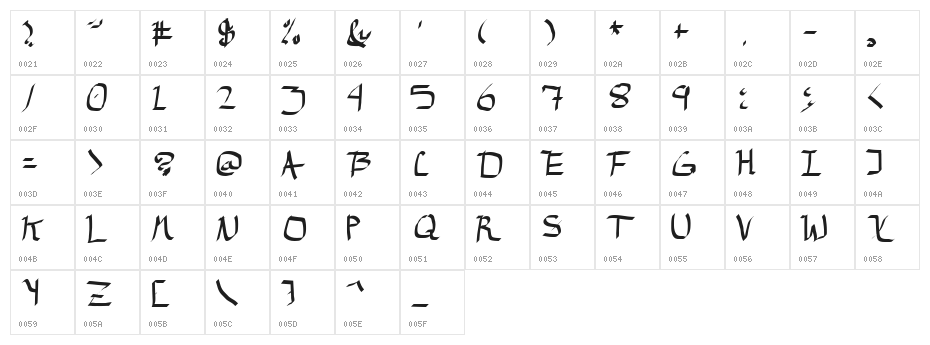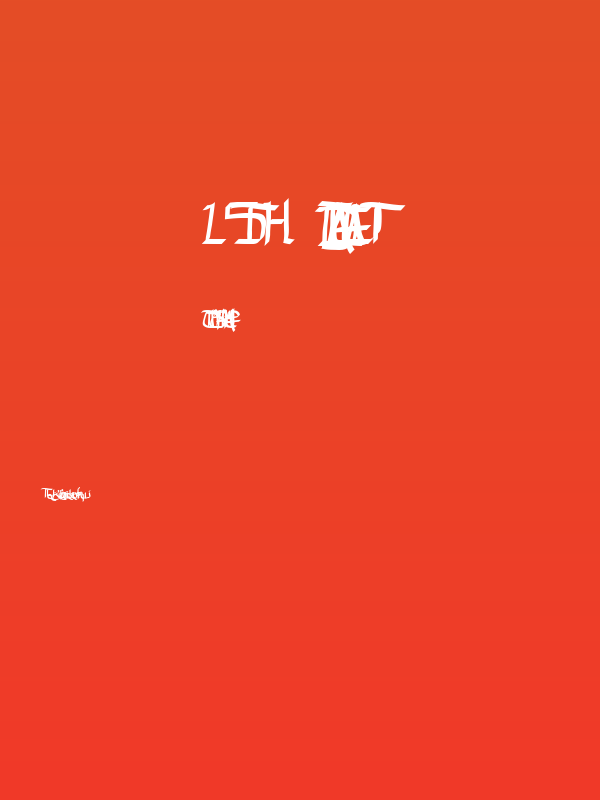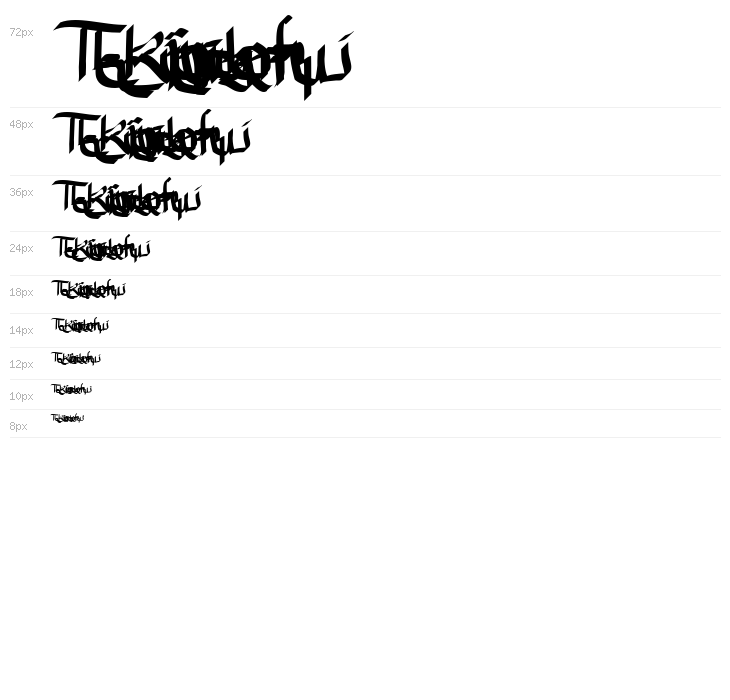
15th Accident Font
| Anwendungsfall | Logos, Headlines, Artistic projects |
| Vorgeschlagene Projekte | Ideal for artistic projects, album covers, posters, and creative branding that require a bold and unique statement. |